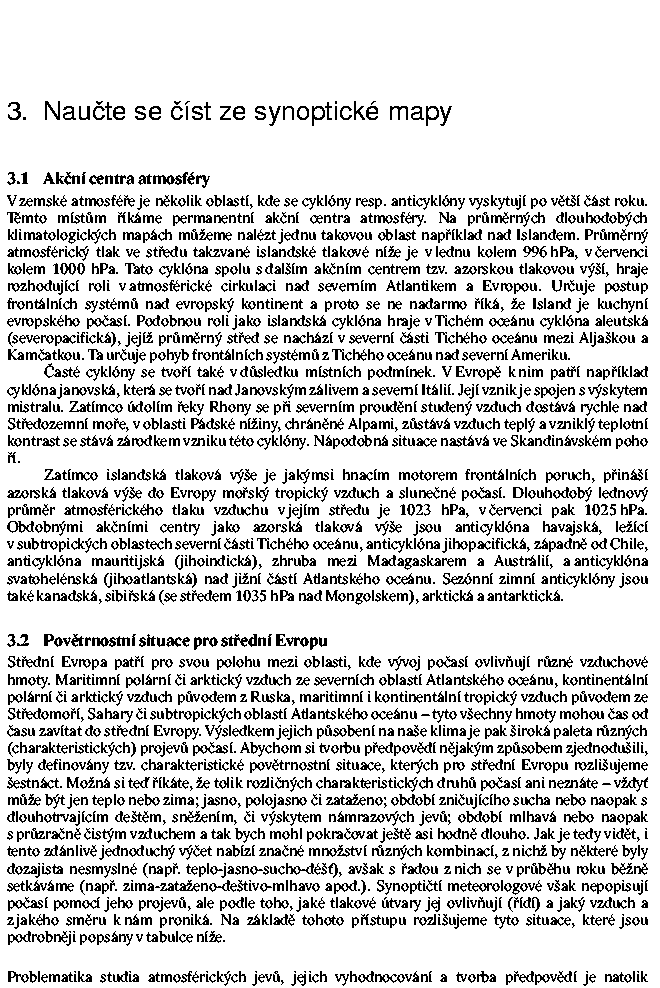
Naprosté základy typografie
1 Naprosté základy typografie
2 Typografie Umění práce s textem při jeho sazbě 500letá historie Nástup počítačů zjednodušení náročné práce, jedním z prvních byl TEX Donalda Knutha (1977) Typografická pravidla usnadňují čtení textu čtenářem Jejich používání je nevynutitelné ČSN stále platí, ale od roku 1999 nemají právní dopad Jsou doplňkem pravidel gramatických
3 Písmo minusky VERZÁLKY KAPITÁLKY Kerning AVATAR vs. AVATAR Slitky Antikva fi vs. fi Grotesk fl vs. fl Neproporciální Rodina řez Normální (vzpřímené) (Polo)tučné Kurzivní, skloněné ij vs. ij Vyznačování Tučné, kurziva Prostrkání VERZÁLKY, KAPITÁLKY
4 Volba písma (1)
5 Volba písma (2)
6 Volba písma (3)
7 Volba písma (4)
8 Volba písma (5)
9 Členění textu Kapitola Podkapitoly Číslování Odstavec Zarážka, východový řádek Oddělování Zarovnávání Mezislovní mezery Dělení slov Stránka parchanty
10 Hladká sazba (1) Pomlčka, spojovník, minus Interpunkce, -,,,.,?,!,... vs. Pomlčka: odděluje části textu (náhrada závorek), až, od do, versus, nesmí být na začátku řádku Těsně za slovo, za nimi mezera (výjimka: čísla, čas, násobení, členění textu) Spojovník: dělení slov, spojování výrazů ( anglicko-český, Frýdek-Místek, není-li, n-tice ), při zlomu řádku v místě spojovníku se opakuje na začátku dalšího řádku Závorky Pořadí (), [], {}, <>, // Přisazují se k textu, který obsahují, od okolí mezerou Uvozovky České: (99-66) (»«)
11 Hladká sazba (2) Stupeň, procento, promile º, %, Jednotka (bez mezery pouze jako přídavné) Palec a stopa ", ' Jednotka +,, = S mezerami Specialita matematické sazby Internetové adresy Většinou bez protokolu Pokud možno v základním tvaru Nevyznačovat, nebo vyznačit špičatými závorkami ( ) Dělení v místě tečky: www. idnes.cz nebo zdvojením speciálního znaku ian.cz/ /clanek2.html (v místě spojovníku je to nebezpečné)
12 Hladká sazba (3) Není mezera jako mezera Čísla Běžná (mezislovní) Desetinná: 2,257 6 Pevná (nedělitelná) číslo a jednotka ve zkratce, titul a jméno, iniciály a příjmení, jednoznakové předložky a spojky, kategorie a pořadí (obr.\3), datum (25.\července), zkratky (a.\s.) Dlouhá: , Zúžená: trojice cifer v dlouhých číslech m et Kos & syn Pokud nemá matematický význam, rozepsat krátké: NE: Na pískovišti si hrály 3 děti. Běžel 5hodinový maratón. Nevhodné kombinovat číslice a slova 6 milionů 576 tisíc 150 nebo 6 milionů Čas hh.mm:ss
13 Seznamy, výčty Bez tečky s malým písmenem Bez tečky s velkým písmenem (prezentace) Jako jednotlivé věty se vším všudy Jako dlouhá věta V balíku bylo nalezeno: 3 kg másla, 6 kg chleba, 30 l vodky a 12 kg střelného prachu. Ale všude stejně! Veškerý materiál byl zabaven.
14 Matematická sazba Lepší použít nějaký editor, který umí rovnice dobře Ruční sazba velmi náročná a náchylná k chybám Řez písma: Vzpřímeně čísla, názvy funkcí a operátorů, indexy, pokud neoznačují proměnnou, jednotky 2h f 3 Bf= 2 c 1 hf kt eff e 1 =C sin cos ln =arctg y x dy 2,35 =m dm + f g ( x)= f ( x) g ( x y)d y Skloněně proměnné (i v běžném textu) B= A, B=0 Tučně vektory E k =25GJ
15 Odlišnosti anglické sazby Pomlčka čtverčíková bez mezer: Double stars called binaries are... Uvozovky (66 99) Jiný algoritmus dělení slov Spojovník bez mezer, nikdy se neopakuje na začátku dalšího řádku Čísla Desetinná tečka, řády se oddělují čárkou 2,205, Řadové s koncovkou (1st i 1st) Zkratky iniciály s tečkami bez mezer (U.S.A), u jmen se sázejí mezery G. B. Shaw i G.B. Shaw Zvláštnosti psaní verzálek on first Monday in October The Application of the Data Processing
16 Citace literatury Články Wolf, M., Zejda, M.: 2005, Astron. Astrophys., 437, Wolf, M., Zejda, M.: Astron. Astrophys, 437 (2005), Wolf, M., Zejda, M. (2005): Apsidal motion in southern eccentric eclipsing binaries: V539 Ara, GG Lup, V526 Sgr and AO Vel, Astron. Astrophys. 437, Monografie Stix, M.: 1989, The Sun An Introduction, Springer-Verlag Berlin Heidelberg Odkazy v textu: [4], Wolf a Zejda (2005), Wolf a Zejda [4]
17 Časté chyby v diplomkách Parchanty - vs. vs., 10x50 vs Jednoznakové spojky a předložky na konci řádku Jednotky skloněně, neodděleny od hodnoty Špatný zápis čísel, % Zlom řádku v místě hodnota / jednotka Špatné rozvržení stránky (moc do krajů, moc nahoru, ) Proměnné v textu nejsou skloněné Vzorečky, obrázky!!!